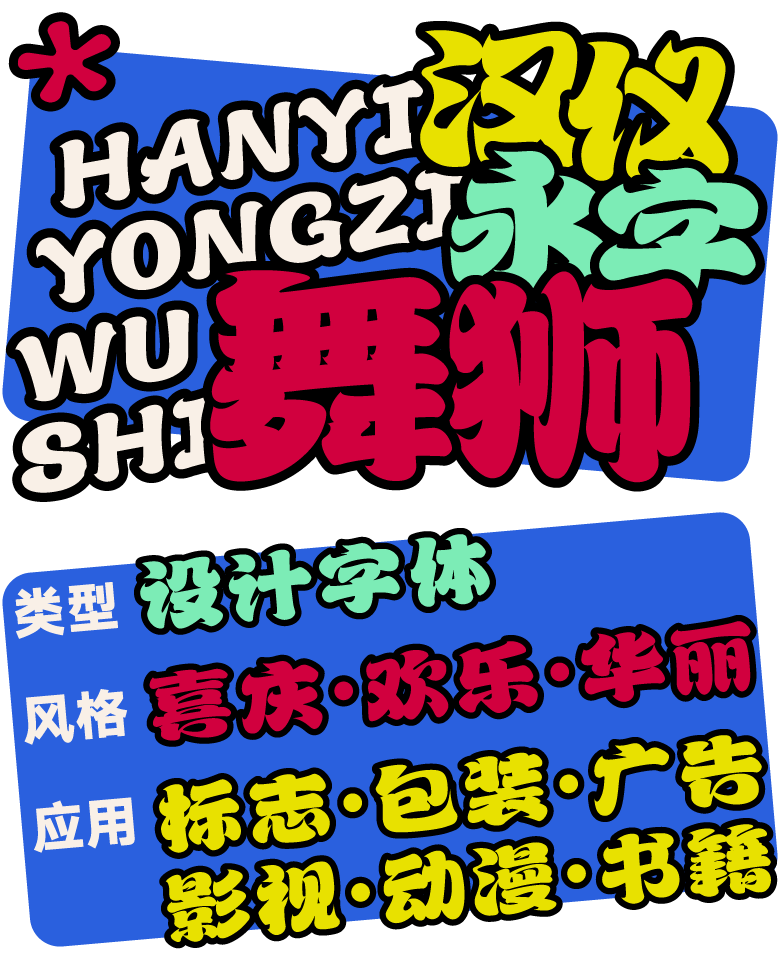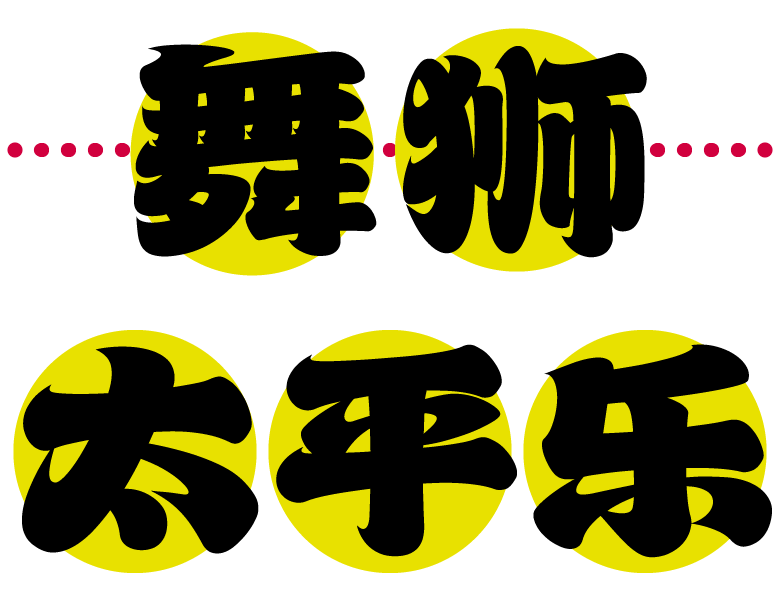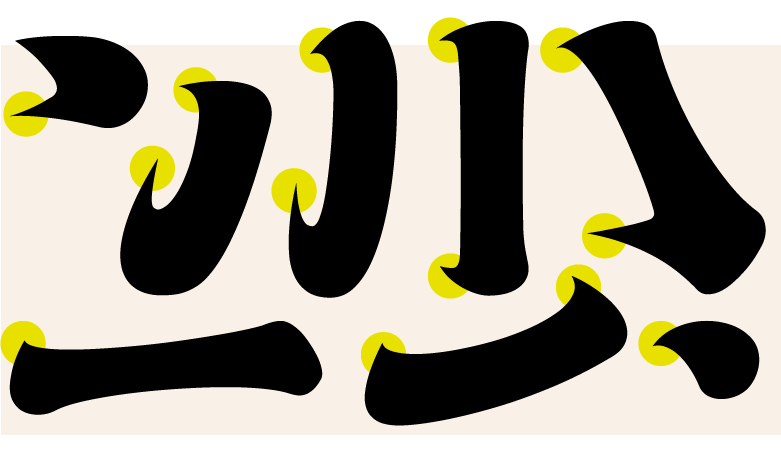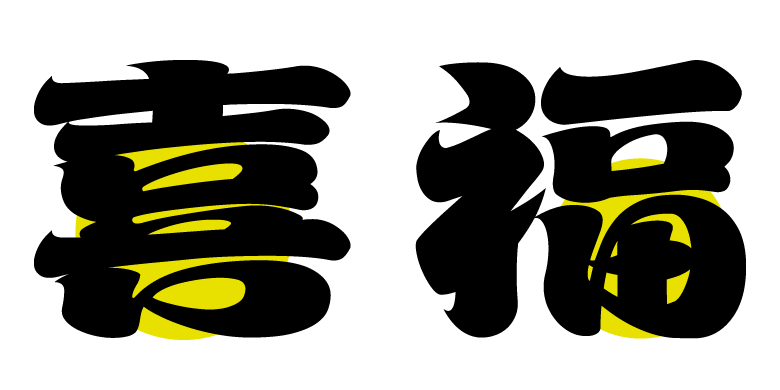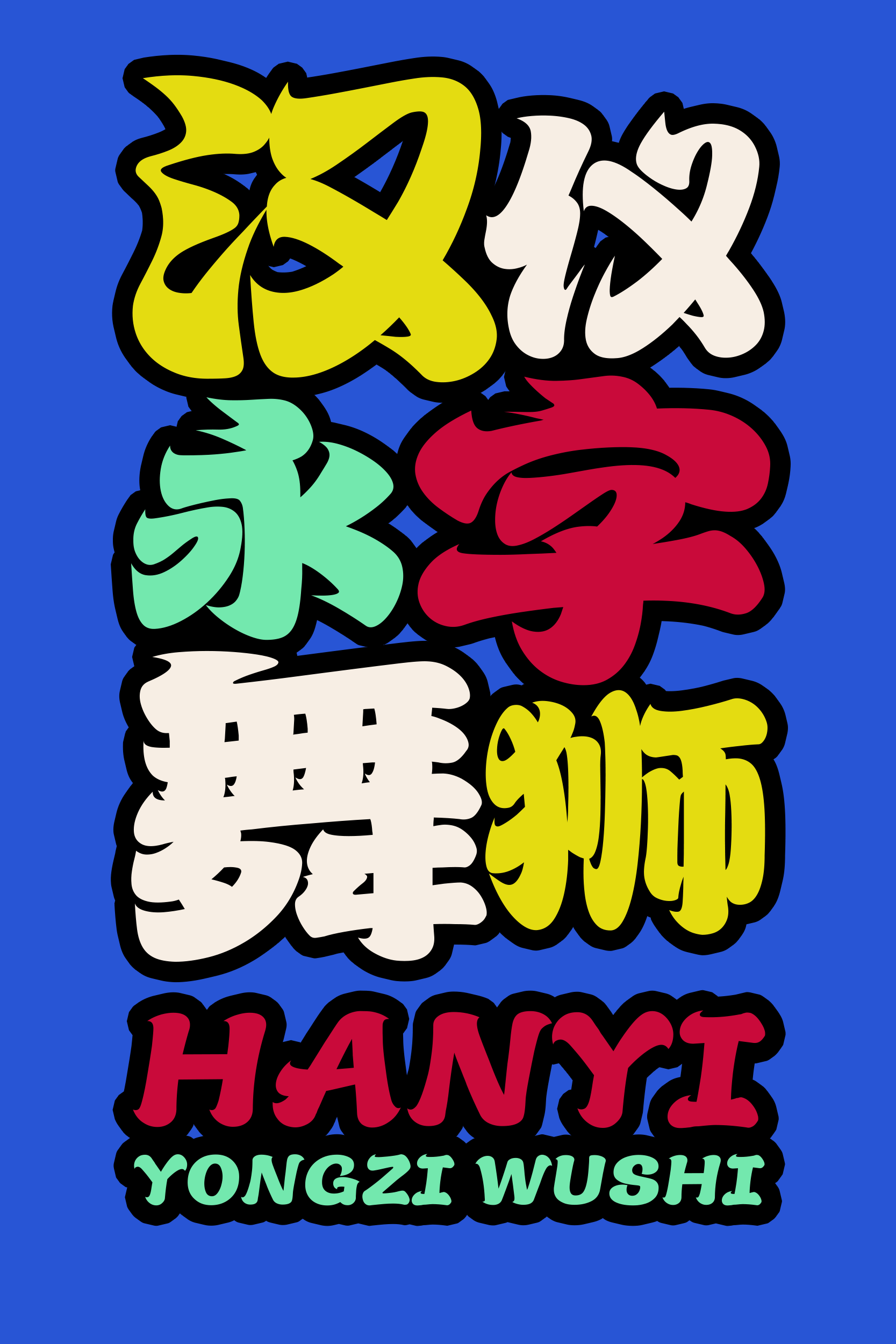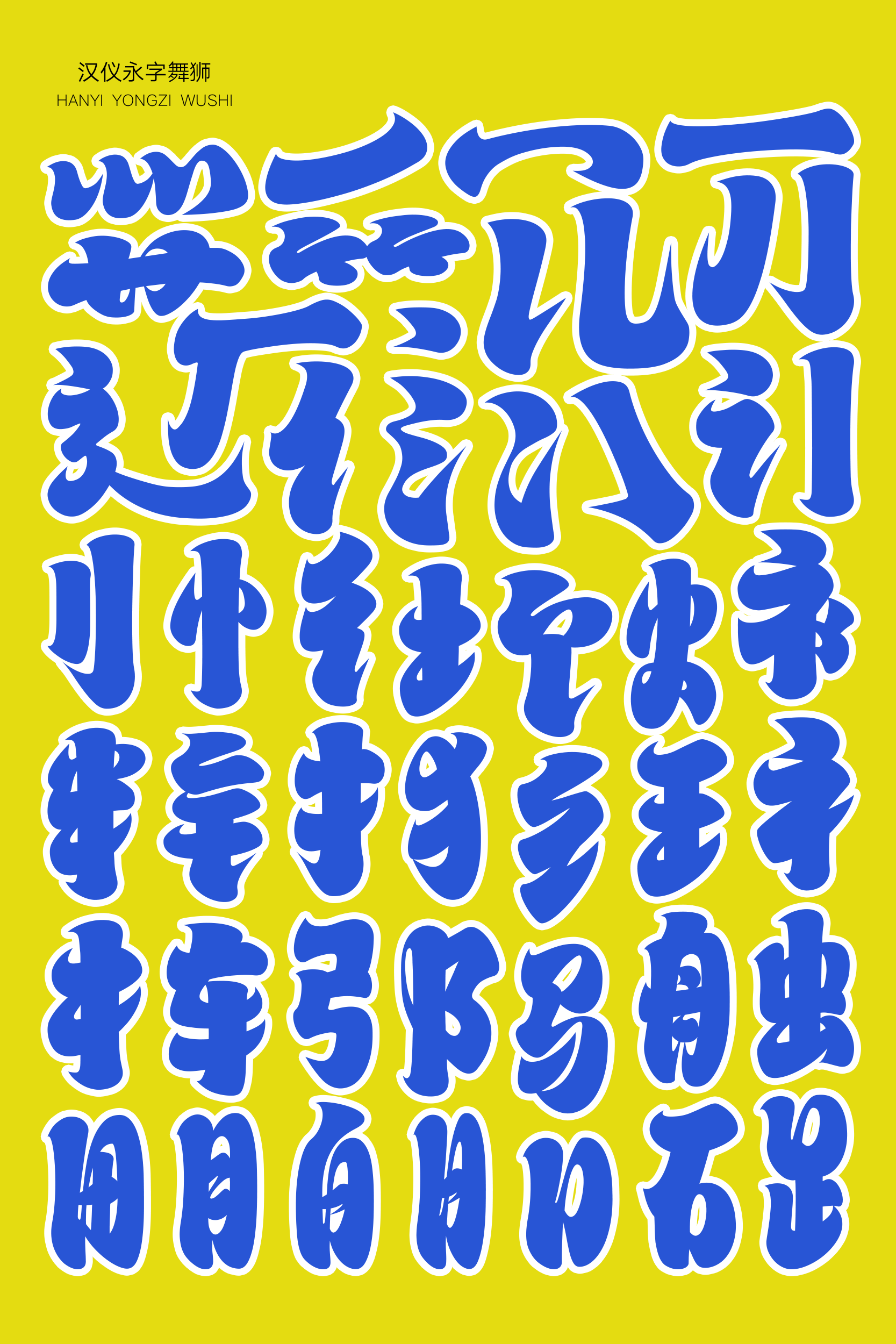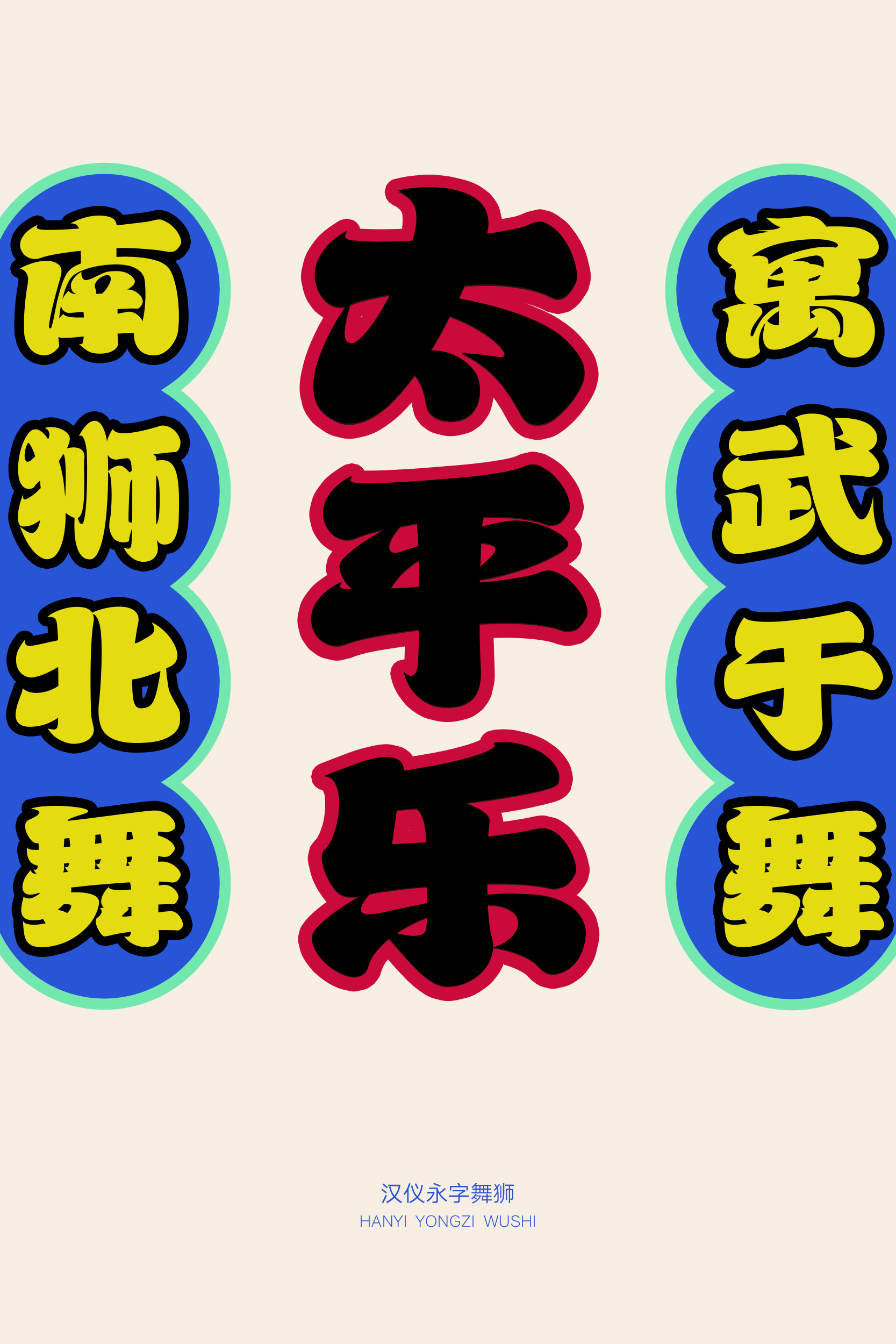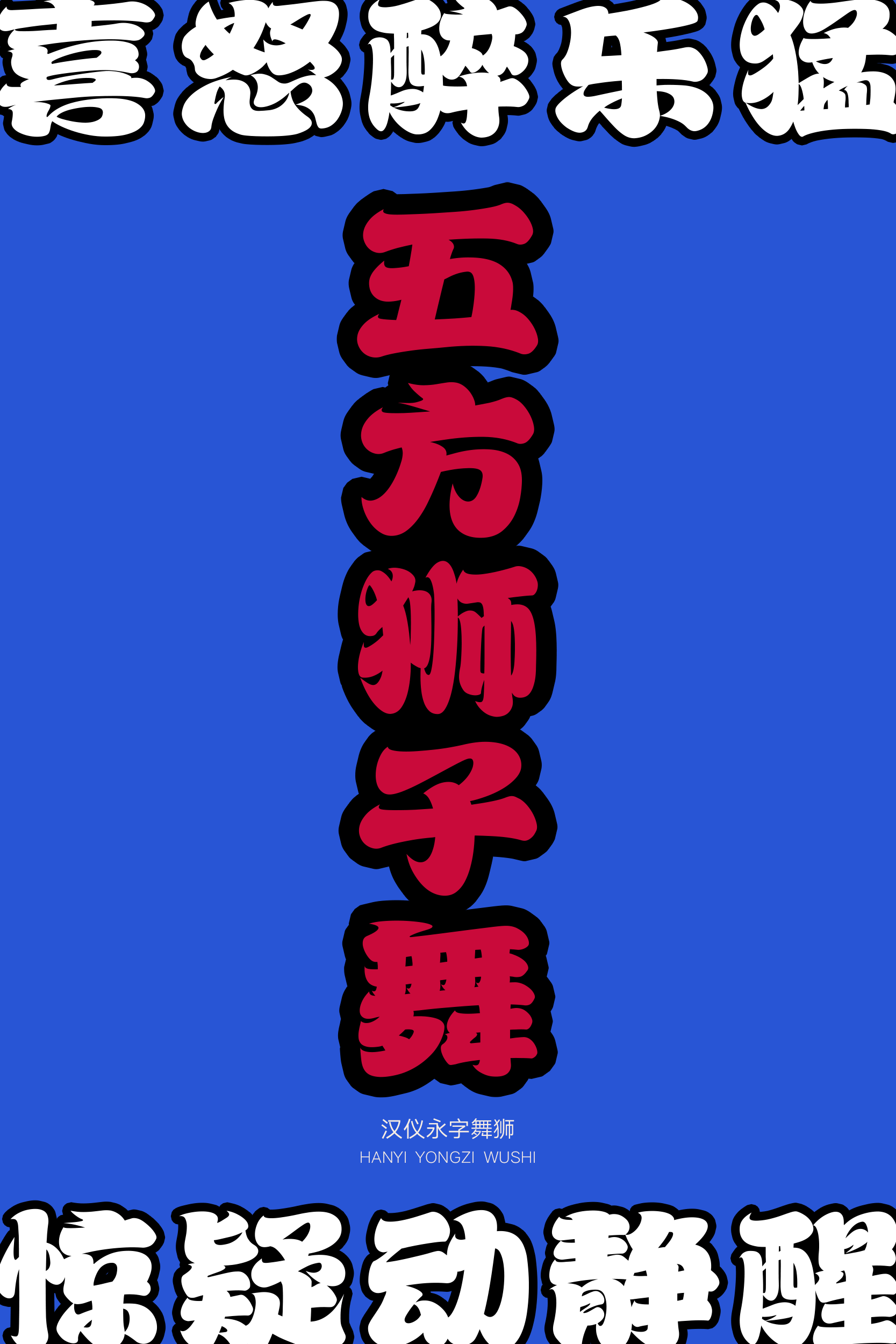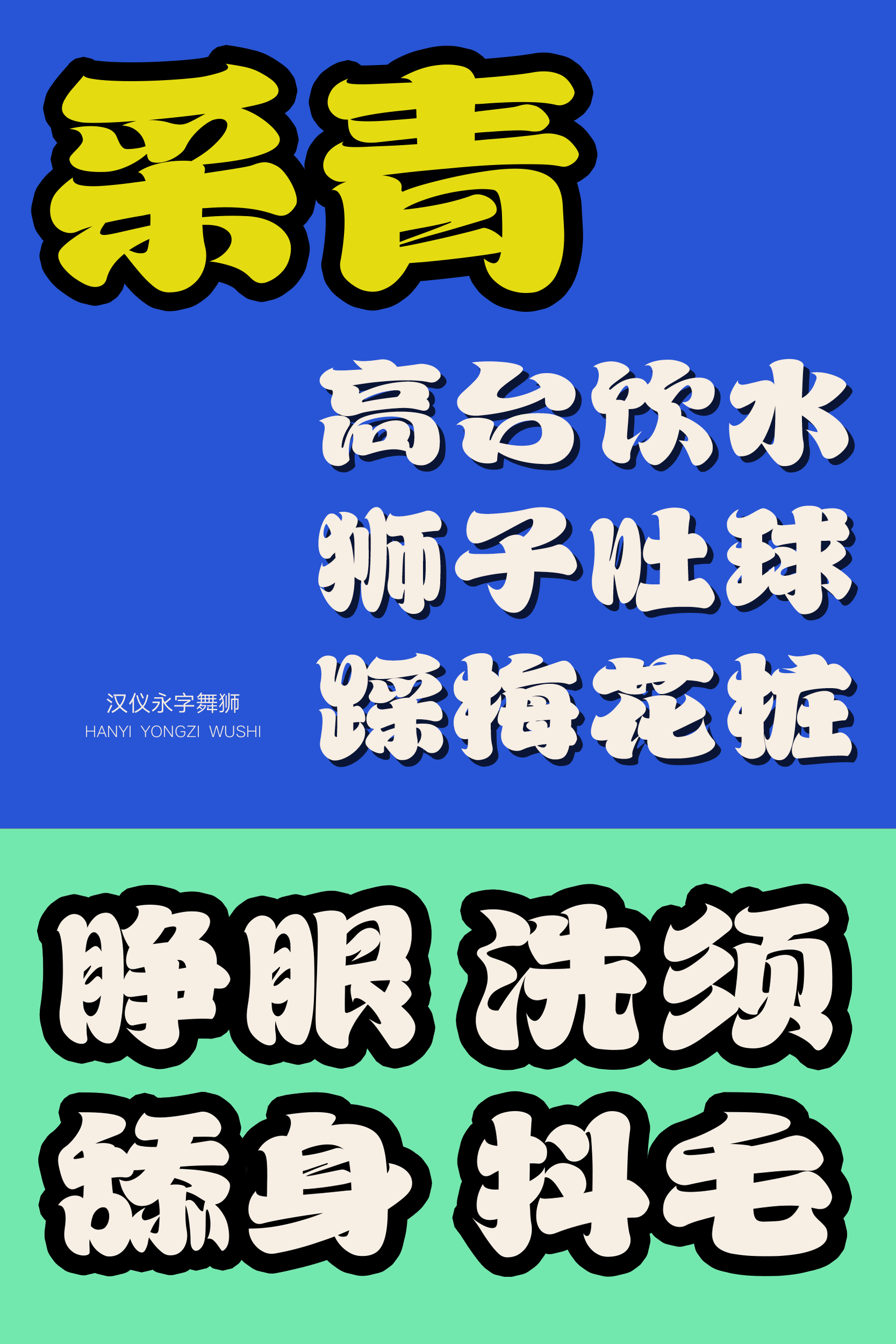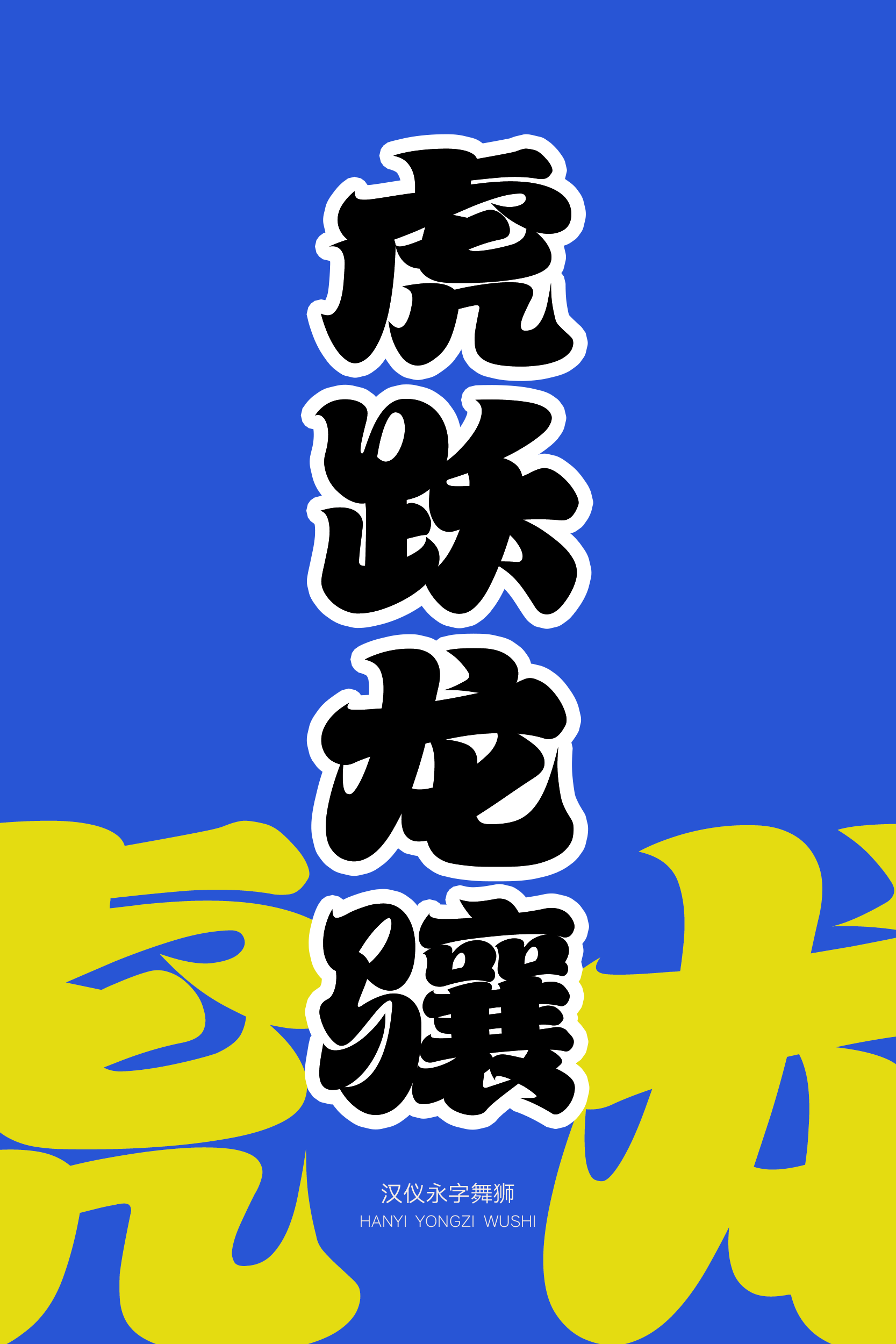
好似舞狮一般的动感书法字体
汉仪永字舞狮是一款富有动感的书法风格设计字体,字体风格喜庆热闹。字形浑圆饱满,笔画华美大气,笔画连带的走向和起收笔飞扬的笔锋营造出如同舞狮一般的动感。这款字体适合作为标题字体用于休闲餐饮、影视娱乐等使用场景,烘托节庆时令的喜乐欢腾的氛围。
字形浑圆饱满,重心平稳。
笔画华美大气,起收笔有着飞扬的笔锋。
笔画连带的走向营造出如同舞狮一般的动感。
汉仪永字舞狮的西文部分与中文部分有着统一的设计语言,字形饱满稳定,起收笔向右上飞扬带出动势,中西文搭配使用渲染出喜庆热闹的氛围。